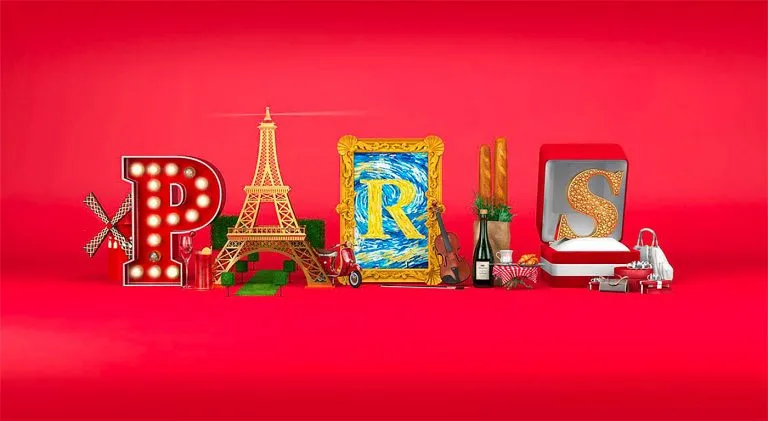
Incríveis tipografias em 3D do designer DUSK
DUSK é um jovem designer especializado em tipografia e ilustração, ele compartilhou recentemente algumas de suas tipografias em 3D e está encantando a todos pela sua criatividade.
Ele adora explorar as variedades de estilos e maneiras para criar a tipografia perfeita, os resultados de suas criações são letras divertidas, coloridas e modernas.
Separamos algumas de suas tipografias para você se impressionar com o talento do jovem designer.